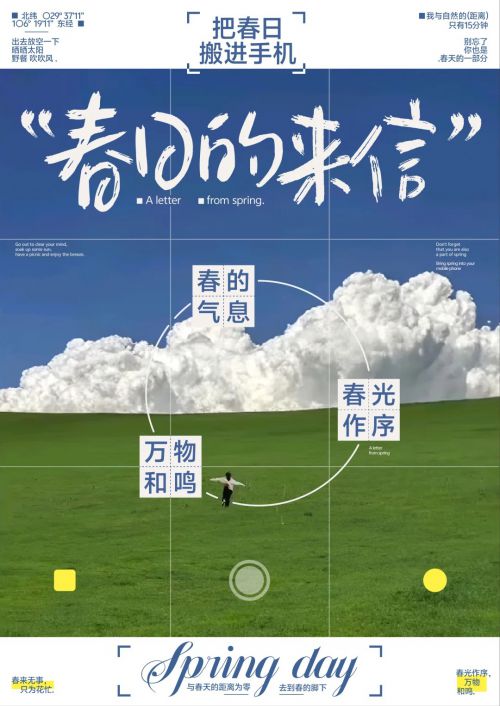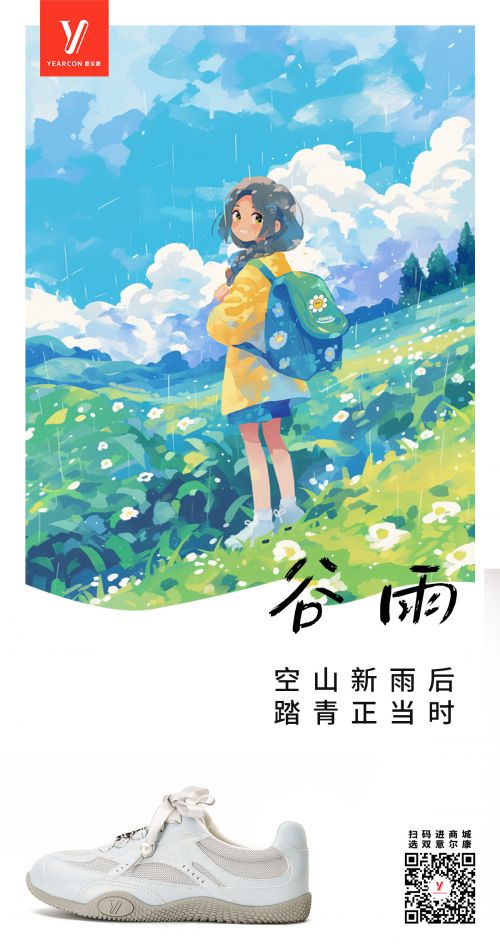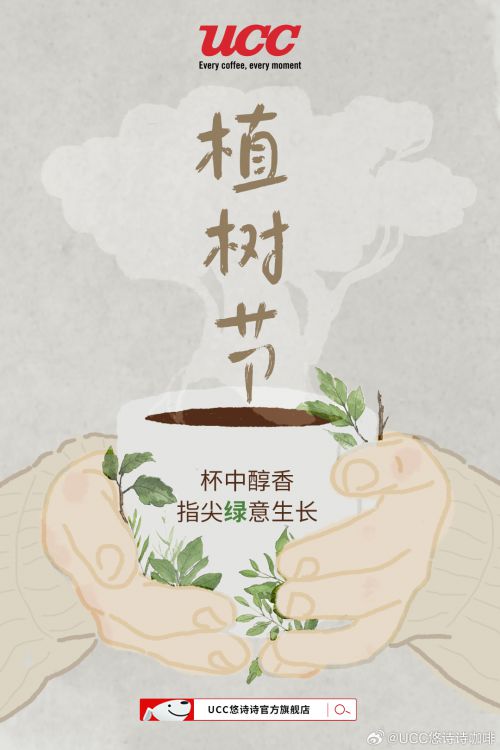
字由随意
字由随意是字由品牌推出的一款手写体字体,融合卡通、可爱、手写风与涂鸦趣味,以轻松灵动的笔韵传递自由活泼的视觉感受。作为专为创意场景打造的手写字体,其字重正常却粗细均匀,粗实笔画中透着随性与活力,仿佛手写时的即兴创作,字里行间跳跃着自由的韵律。 字由随意在结构设计上兼具方正形态与宽博中宫,重心居中的排布让字体既稳定又舒展,适合多场景排版需求。笔型融入俏皮斜切设计,方头笔画搭配自然断开的笔触,打破传统手写体的规整感,每一笔都似随手涂鸦般生动,卡通感与手写温度并存,轻松营造可爱有趣的视觉氛围。 无论是卡通主题海报、儿童文创设计,还是社交媒体趣味配图,字由随意都能以鲜活的字形点亮画面。支持会员商用授权的它,不仅兼顾设计美感与实用价值,更以“随意”为名的自由气质,成为手写体爱好者与设计师捕捉创意灵感的优选字体。